Die Ultimative Anleitung für die perfekte Happy Birthday Schrift
Von klassisch bis modern: So wählen Sie den richtigen Ton für Ihre Glückwünsche.
Geburtstage sind emotionale Meilensteine. Wir verbringen Stunden damit, das richtige Geschenk zu suchen und den perfekten Kuchen zu backen. Aber wie oft unterschätzen wir die Macht der Worte – oder besser gesagt, wie diese Worte aussehen? Eine lieblos getippte Nachricht wirkt schnell kalt.
Eine sorgfältig ausgewählte Happy Birthday Schrift hingegen verwandelt einen einfachen Glückwunsch in eine persönliche Umarmung aus Papier. Egal, ob Sie eine Karte basteln, ein T-Shirt bedrucken oder einen digitalen Gruß versenden: Die Typografie setzt den Ton für die gesamte Feier.
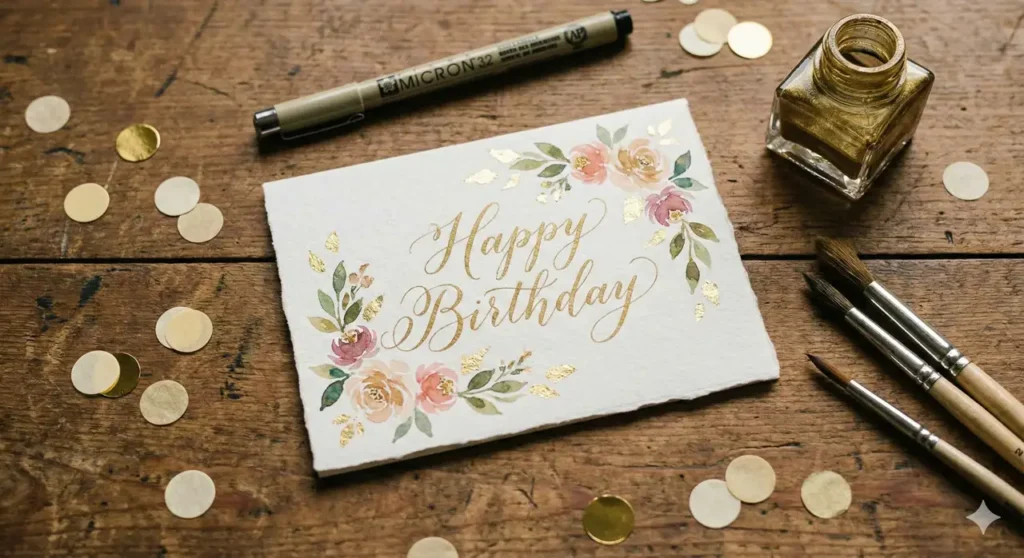
Warum die Wahl der Schriftart (Font) so wichtig ist
Haben Sie schon einmal eine Einladung zu einer eleganten Abendparty in einer krakeligen Comic-Schrift erhalten? Es passt einfach nicht. Schriften haben Persönlichkeiten.
- Serifen-Schriften (wie Times New Roman) wirken traditionell und respektvoll.
- Schreibschriften (Script Fonts) strahlen Eleganz und Wärme aus.
- Handgeschriebene Fonts wirken verspielt, persönlich und nahbar.
“Wenn Sie ‘Happy Birthday’ schreiben, wollen Sie Freude vermitteln. Deshalb funktionieren statische Standardschriften hier selten gut.”
Top 3 Kategorien für Happy Birthday Fonts
Wenn Sie auf der Suche nach der passenden digitalen Schriftart sind, orientieren Sie sich an diesen drei Stilrichtungen. Die meisten dieser Fonts finden Sie kostenlos auf Google Fonts oder DaFont.
1. Der elegante Klassiker
Perfekt für runde Geburtstage (30., 50., 60.) oder formelle Einladungen. Diese Schriften imitieren die klassische Federführung.
Empfehlung: Great Vibes oder Allura.
2. Der verspielte Freund
Dies ist der populärste Stil. Er sieht aus, als wäre er mit einem Pinsel gemalt worden – locker, dick und voller Energie.
Empfehlung: Pacifico oder Lobster.
3. Der moderne Minimalist
Für das designbewusste Geburtstagskind. Hier stehen klare Linien im Vordergrund, oft kombiniert mit viel “Weißraum”.
Empfehlung: Montserrat oder Open Sans.
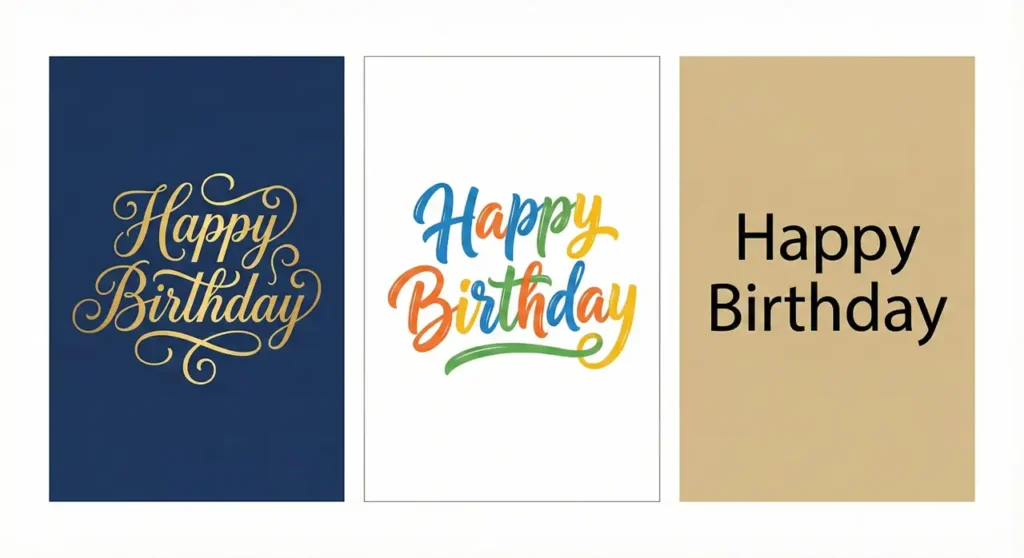
DIY Tutorial: Happy Birthday Schrift selbst gestalten
Sie brauchen keinen Computer, um Eindruck zu schinden. “Hand Lettering” ist der Trend, Buchstaben kunstvoll zu zeichnen. Hier ist eine einfache Anleitung für Anfänger, um den “Faux Calligraphy” (Falsche Kalligrafie) Look zu erzeugen.
Was Sie brauchen:
- Einen einfachen Fineliner (schwarz)
- Ein Stück glattes Papier oder Karton
Das Grundgerüst: Schreiben Sie “Happy Birthday” in Ihrer ganz normalen Schreibschrift. Lassen Sie dabei etwas mehr Platz zwischen den Buchstaben als gewöhnlich.
Die Verdickung: Zeichnen Sie nun bei jedem Strich, der nach unten führt (Abstrich), eine zweite Linie daneben.
Beispiel: Beim kleinen “h” ist der lange Strich nach unten doppelt, der Bogen nach oben bleibt einfach.
Das Ausmalen: Füllen Sie den Hohlraum zwischen den doppelten Linien aus.
Der Feinschliff: Fügen Sie kleine Punkte, Sterne oder Schnörkel um den Schriftzug herum hinzu.
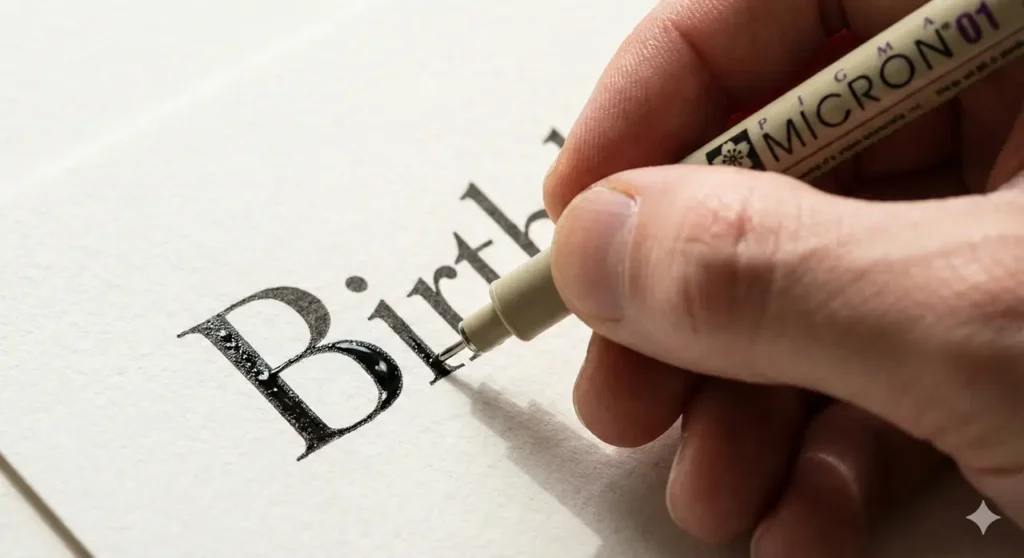
- Cricut Design Space: Für alle, die gerne basteln (Plotten). Hier gibt es spezielle “Single Line Fonts”.
Häufige Fehler, die Sie vermeiden sollten
- ❌ Zu viele Schriftarten: Mischen Sie niemals mehr als zwei Schriftarten. Eine für die Überschrift, eine für den Text.
- ❌ Mangelnder Kontrast: Achten Sie auf starke Kontraste (z.B. Gold auf Dunkelblau).
- ❌ Urheberrecht ignorieren: Viele “kostenlose” Schriften sind nur für den privaten Gebrauch.
Fazit: Machen Sie es persönlich
Ob Sie nun eine Schriftart herunterladen oder selbst zum Stift greifen: Das Wichtigste an der Happy Birthday Schrift ist die Intention dahinter. Nehmen Sie sich die fünf Minuten Zeit, um etwas auszuwählen, das wirklich zum Geburtstagskind passt. In einer Welt voller schneller WhatsApp-Nachrichten ist eine schön gestaltete Karte eines der wenigen Dinge, die man für immer aufbewahrt.